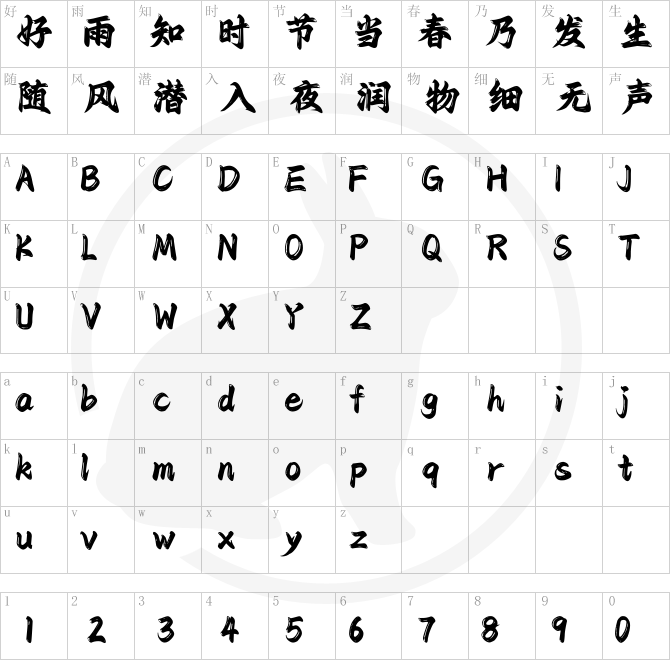
Aa旺财招牌体
Aa旺财招牌体,这款字体结构工整、笔画清晰,兼顾美观与易读性,适用于标题、正文、海报、包装、LOGO 等多种场景。字形优雅稳定,风格百搭耐看,适配日常排版与创意设计,让文字呈现更舒适、更具质感。Aa旺财招牌体一笔一画,皆是细节,以均衡的比例、流畅的线条打造舒适视觉体验,字形端正大气,风格简约现代。无论是商业设计、品牌宣传还是日常排版,都能轻松驾驭,让文字更有格调与力量。Aa旺财招牌体字体下载。